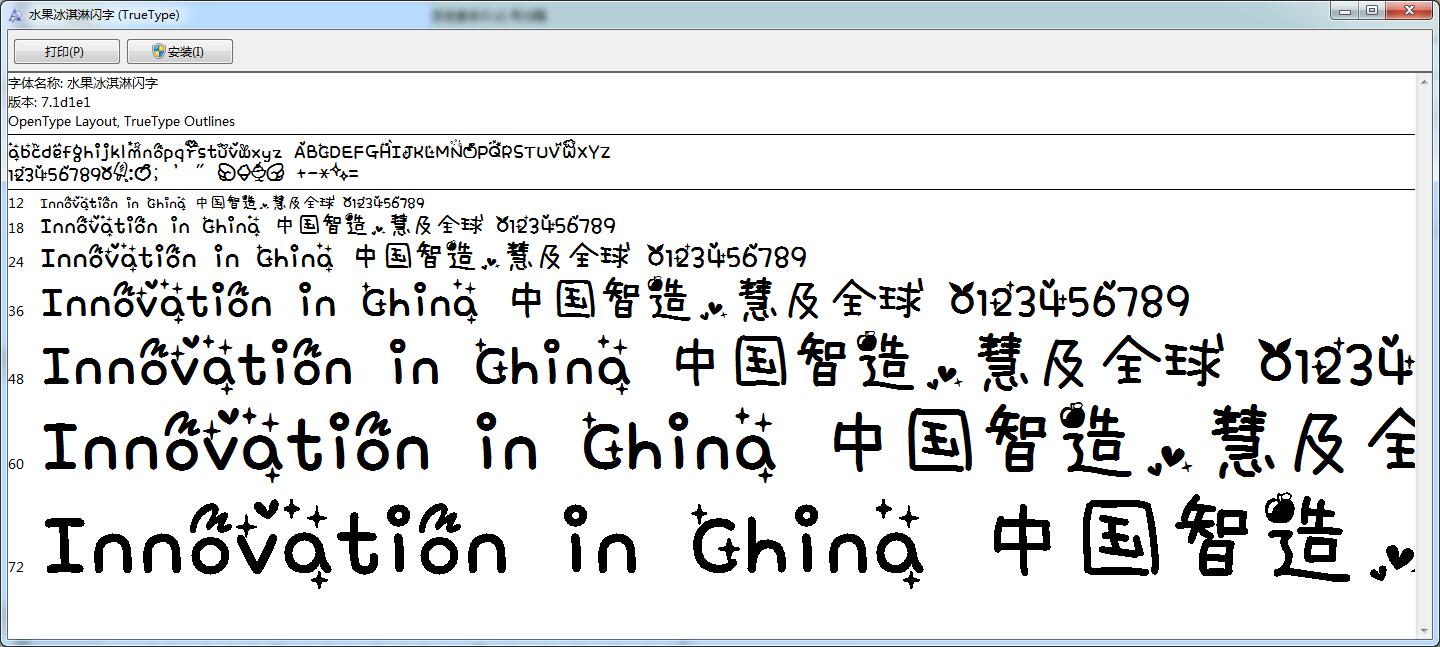
水果冰淇淋字體是一款備受女孩們喜愛(ài)的字體應(yīng)用,使用這款字體的軟件輸出的文字可以輸出愛(ài)心、星星等元素,可以用它來(lái)制作賀卡、發(fā)祝福等等,喜歡這款字體的用戶歡迎在綠色資源網(wǎng)下載使用!
水果冰淇淋字體是一款比較可愛(ài)的中文字體,它能夠在文字中顯示星星、愛(ài)心、蘋(píng)果、圓形等可愛(ài)元素,很受女孩們的喜愛(ài)!也可以用來(lái)制作藝術(shù)字或者祝??ㄆ?!